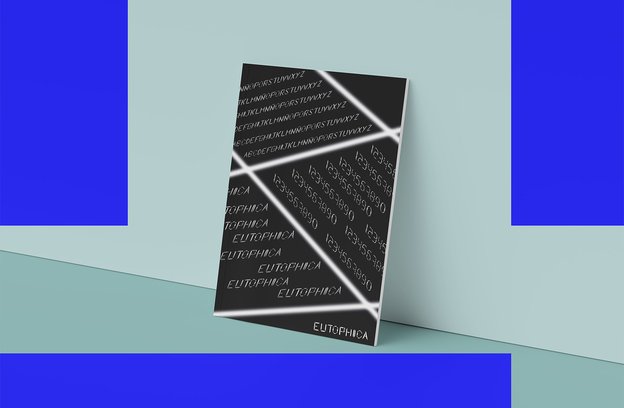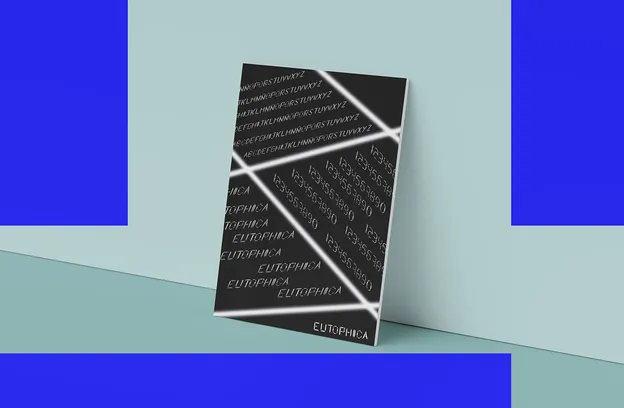
Diseño de una tipografía display como Trabajo Fin de Grado, inspirada en la obra Utopía de Tomás Moro, que interpreta visualmente el concepto de lo utópico mediante investigación conceptual y desarrollo formal.
Esta actividad consistió en el diseño de una tipografía display para una sección de una exposición dedicada al concepto de utopía, tomando como punto de partida la obra Utopía de Tomás Moro.
El objetivo era interpretar visualmente este concepto a través de una propuesta tipográfica que no solo comunicara, sino que también expresara una visión personal de lo utópico. El proceso incluyó una fase de investigación conceptual, la elaboración de un mood board y el desarrollo formal de la tipografía.